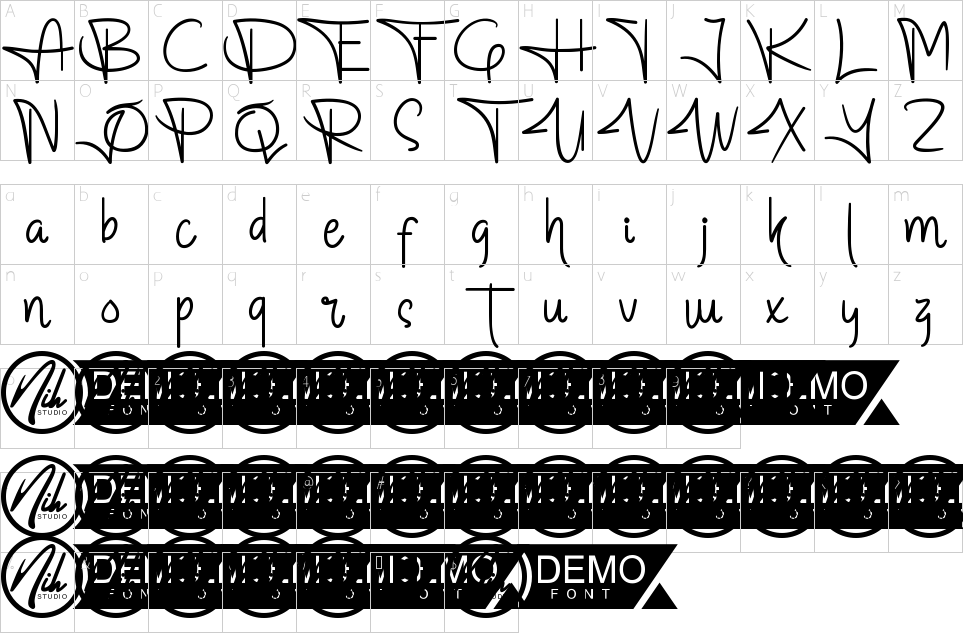
A fonte Marlinton é um presente para designers e criadores de conteúdo, projetada com cuidado para criar textos agradáveis e atraentes. Se você busca uma fonte grata para seu próximo projeto, Marlinton é um ótimo escolha. Desenhada pela equipe dedicada do nihstudio, que também criou outras fontes únicas, Marlinton foi feita para proporcionar um tom de conforto e elegância. Seu design simples e limpo torna-a perfeita para uso em títulos e subtítulos, ou mesmo como fonte principal para seus projetos. Com mais de mil downloads, é evidente que a comunidade de criativos gosta bastante de Marlinton. Seja para aplicativos, websites ou qualquer projeto em que você precise de uma fonte legível e agradável, Marlinton é uma fonte de qualidade que merece uma oportunidade.